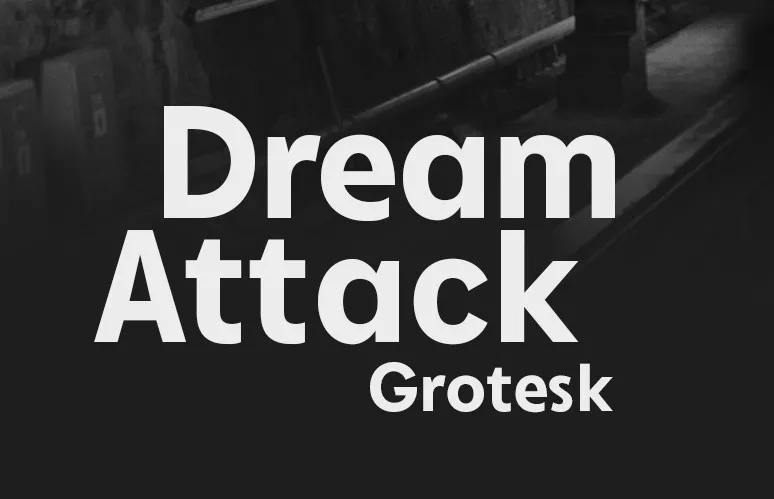
Descubra uma nova escolha para sua próxima projeto de design – a Dream Attack Grotesk Font. Inspirada nos anos 80 e 90, essa sans serif foi projetada por Rafael Nogueira com um estilo inovador e audacioso que combina elementos do rock progressivo e da música eletrônica. Com um ar musical e vibrante, essa fonte é perfeita para qualquer tipo de projeto gráfico – seja web, impressão ou até mesmo design em movimento. Ideal para adicionar um toque diferenciado a peças como camisetas, postais, logomarcas e muito mais, Dream Attack Grotesk oferece uma forte personalidade que certamente fará seu trabalho. E, claro, não podemos esquecer de mencionar sua versatilidade: ela se adapta perfeitamente para qualquer projeto gráfico que você possa imaginar.